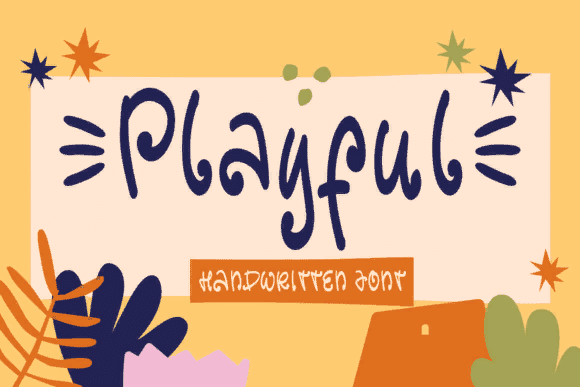
Playful
- это милый и причудливый рукописный шрифт.
Он воплощает игривость и подлинность и идеально подходит для любого детского мероприятия или школьного проекта.